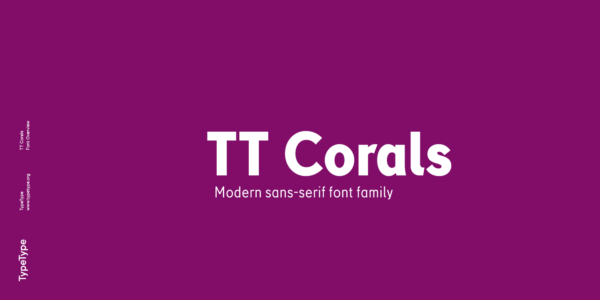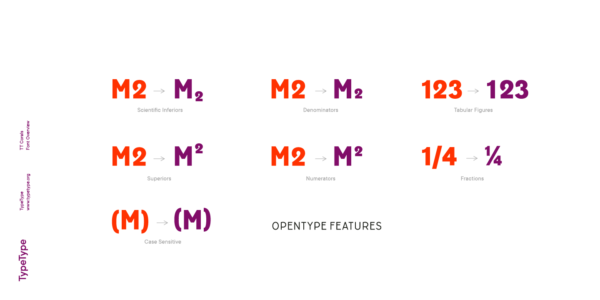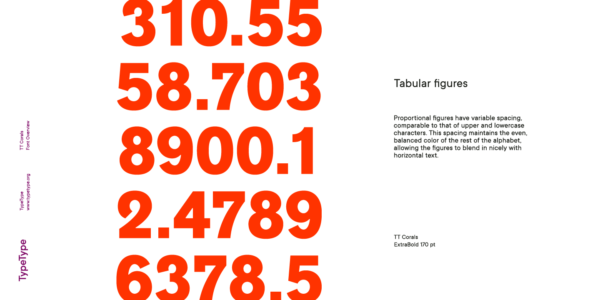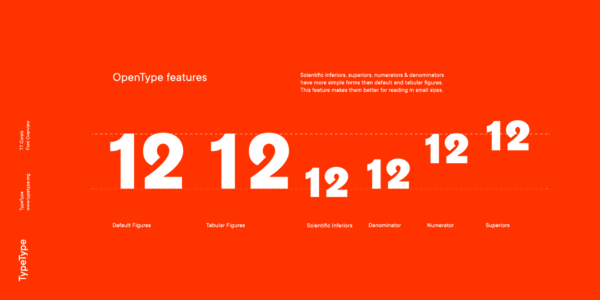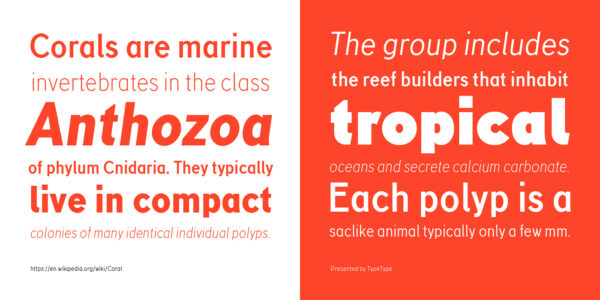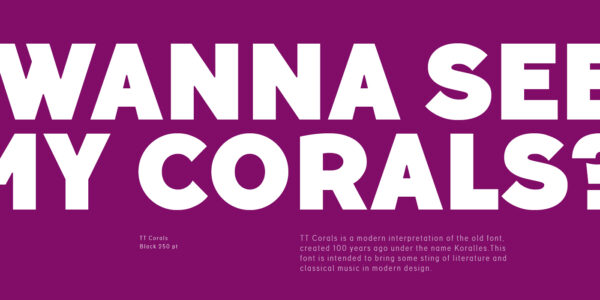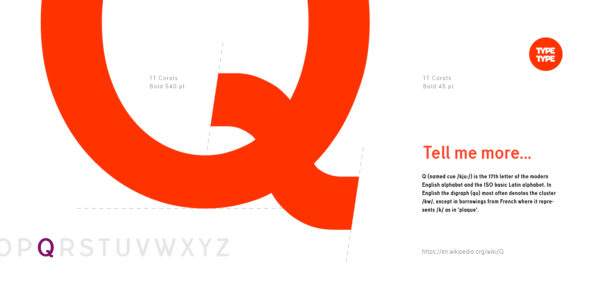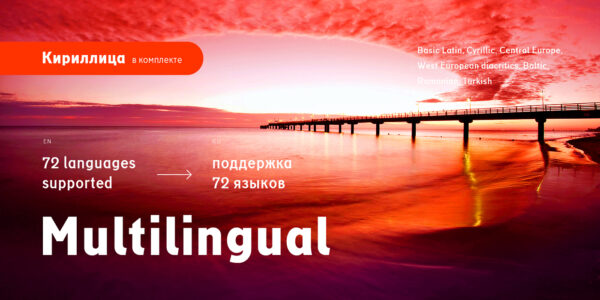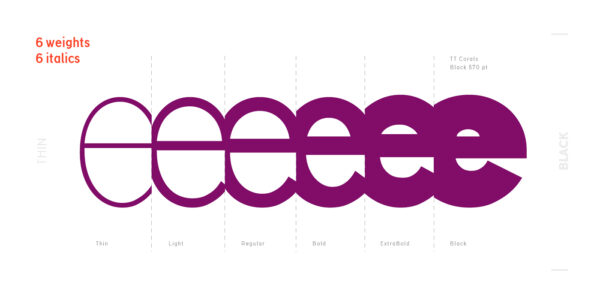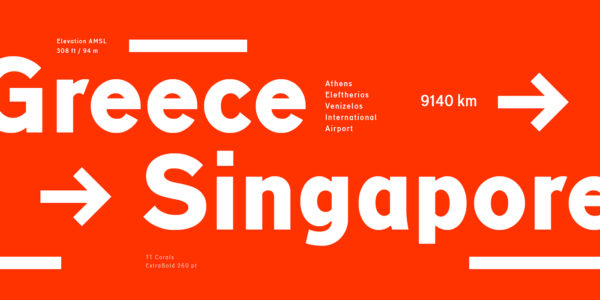
TT Corals
TT Corals — ТТ Коралс
Произносится «ТТ Коралс». «Corals» — производное слово от coral, в переводе с английского «корал». Буквы «TT» являются аббревиатурой названия компании.
TT Corals — современный гуманистический гротеск, в котором сохранились характерные исторические черты шрифтов начала XX века.
TT Corals
Современный гуманистический гротеск
Для большей функциональности шрифтового семейства, мы создали 6 различных вариаций начертаний по толщинам: Thin, Light, Regular, Bold, Extra Bold, Black. Характерная плавность линий и отдельных элементов позволяет использовать TT Corals в самых разнообразных областях дизайна. TT Corals вдохновляет своей свежестью и новизной, а также дарит новые идеи для вашего творчества.
TT Corals
TT Corals имеет очень много характерных исторических черт начала 20-го века
TT Corals
Шрифт хорошо подойдет для классической литературы или музыки
О гарнитуре TT Corals
TT Corals — это современный гуманистический гротеск, который имеет очень много характерных исторических черт начала 20-го века. Для большей функциональности шрифтового семейства, мы создали 6 различных вариаций начертаний по толщинам: Thin, Light, Regular, Bold, Extra Bold, Black.
Характерная плавность линий и отдельных элементов позволяет использовать TT Corals в самых разнообразных областях дизайна. Например, он очень хорошо подойдет для темы классической литературы или музыки, а также для других самых разнообразных творческих областей человечества. TT Corals вдохновляет своей свежестью и новизной, а также дарит новые идеи для вашего творчества.
case | Case Sensitive Forms
({[H]})
frac | Fractions
1/2 3/4
numr | Numerators
H123
dnom | Denomerators
H478